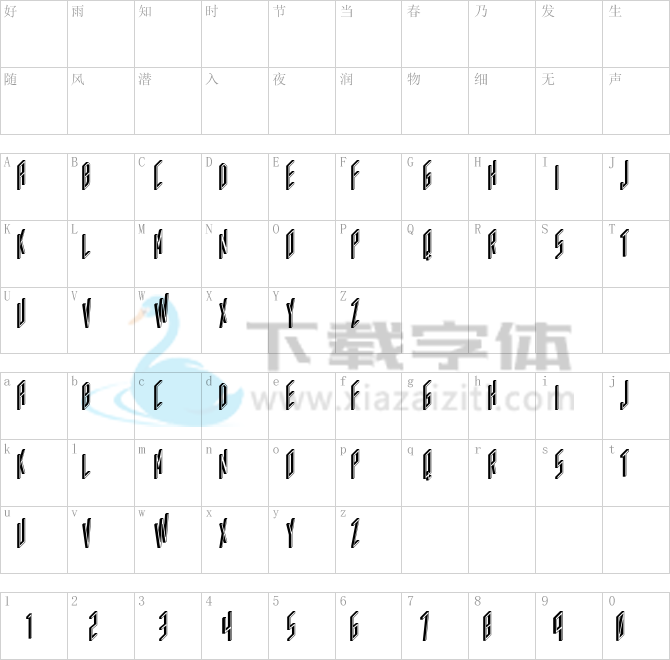
AC Framed.otf字体下载,这款字体结构工整、笔画清晰,兼顾美观与易读性,适用于标题、正文、海报、包装、LOGO 等多种场景。字形优雅稳定,风格百搭耐看,适配日常排版与创意设计,让文字呈现更舒适、更具质感。AC Framed.otf字体下载一笔一画,皆是细节,以均衡的比例、流畅的线条打造舒适视觉体验,字形端正大气,风格简约现代。无论是商业设计、品牌宣传还是日常排版,都能轻松驾驭,让文字更有格调与力量。AC Framed.otf字体下载字体下载。